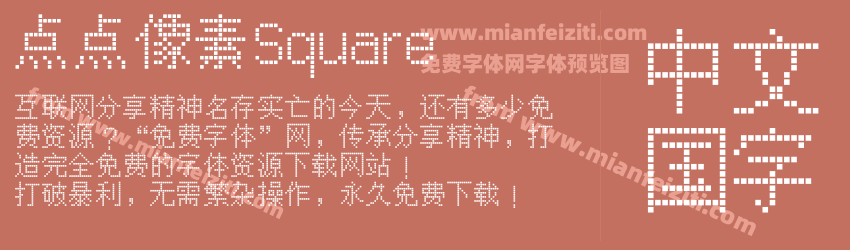
「点点像素」是一个在GPL 2.0协议下免费开源发布的,涵盖超过22000字形的大字符集中文像素艺术字体。
「点点像素」是基于同样以GPL 2.0协议开源的自由字体「文泉驿点阵宋体」,经自动矢量化转换,变形和美化得到的。「点点像素」使用的将点阵字体自动转换为OpenType字体的源代码也已开源。
目前可见的中文像素艺术字体大多有商业许可协议保护,且很多无法涵盖GBK字符集中的全部汉字字形。「点点像素」及其转换工具提供了从开源点阵字体生成开源像素艺术字体的另一种可能。
前几天我为我们举办的DeeCamp人工智能训练营设计宣传海报的时候,想走复古风,用像素艺术字体来写主要的宣传语。发现网上可找到的一些像素字体,往往都有商业许可协议的保护,或者在制作上只包含GB2312这样的基础字符集。
程序员就喜欢自力更生。就动手写了一个JavaScript转换工具,基于著名的开源字体项目「文泉驿」创建的点阵宋体汉字(目前用的是10pt字型的版本),自动完成所有22000多个字形的矢量化,自动将点阵像素变形为不同修饰风格。
代码写得比较简单。目前发布的v0.1版本的「点点像素」字体只能说初具像素艺术字体的基本模样,大体可用,但后续还有很多优化空间。之后有时间时,会继续优化这个项目,用自动化代码创建更多有趣的字体。